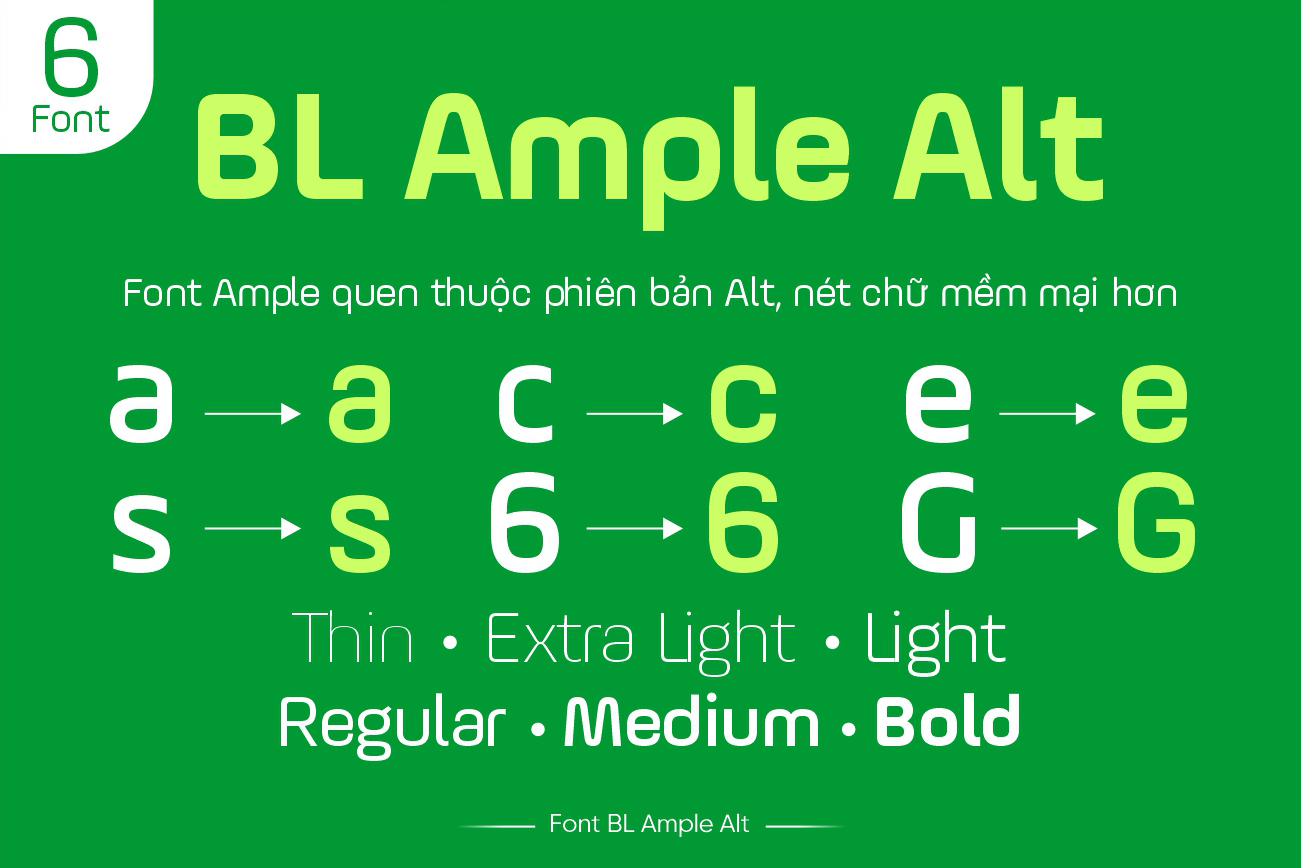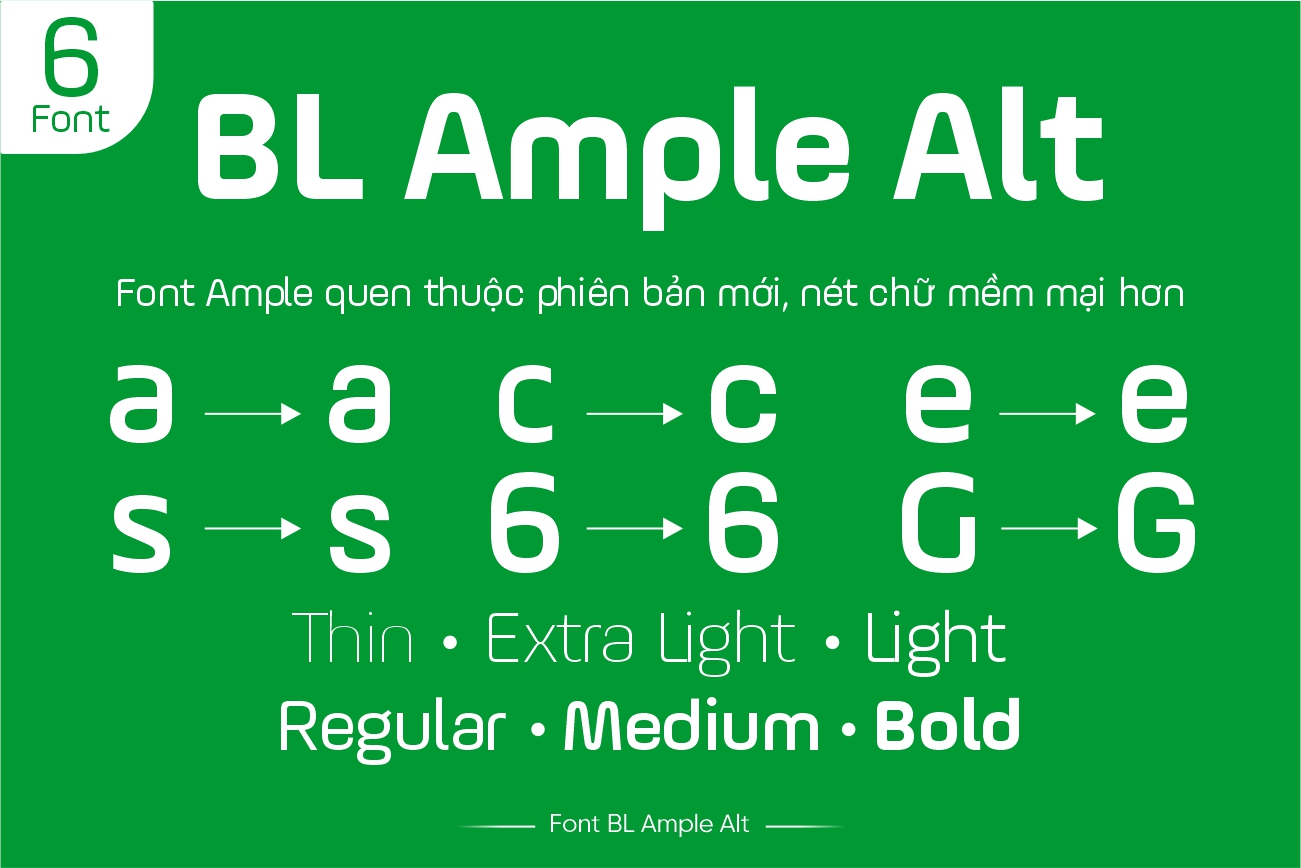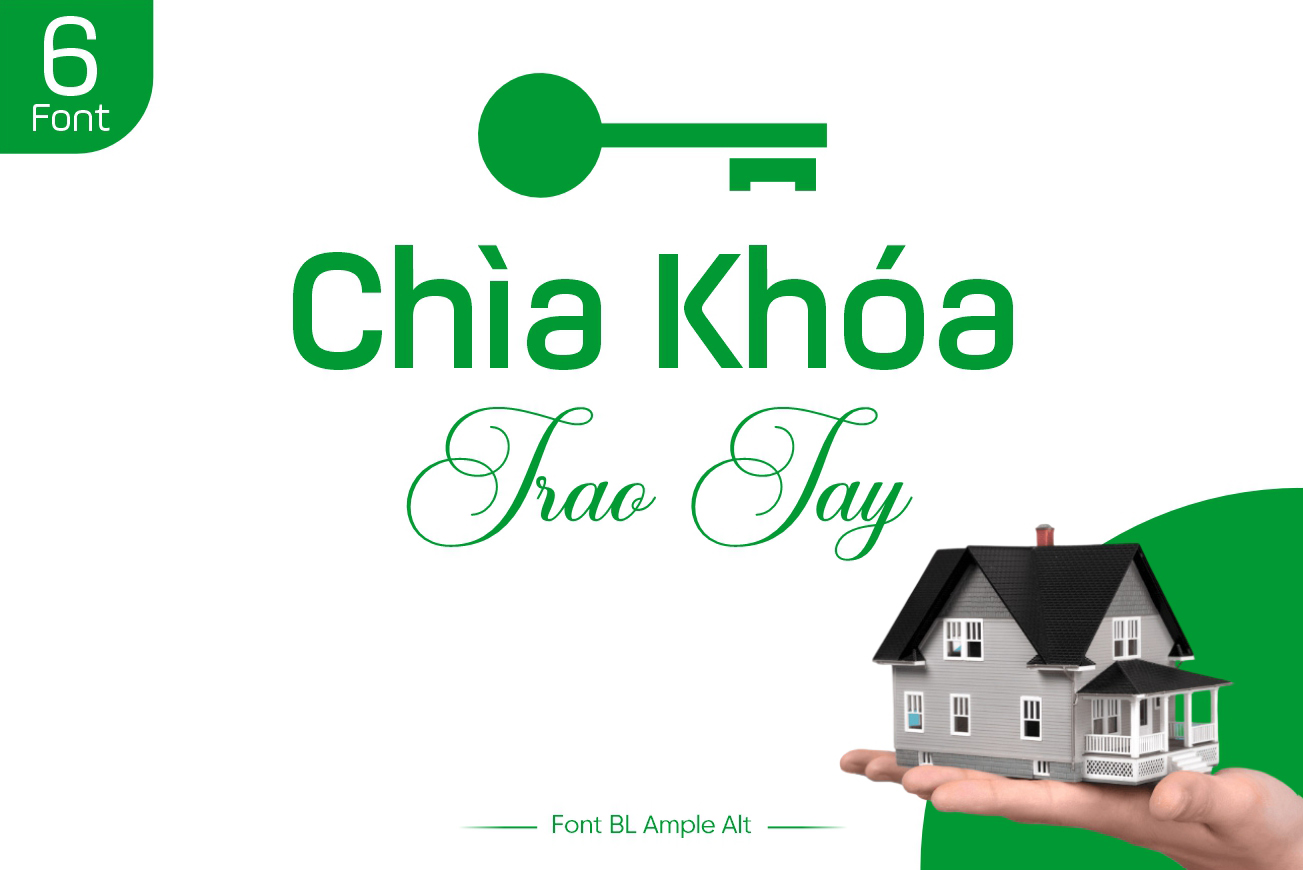
Bộ 6 font BL Ample Alt - Font công nghệ Việt hóa
Tác giả Soneri Type
BL Ample Alt là phiên bản Việt hóa từ bộ font Ample Alt do Soneri Type phát triển, thuộc họ Ample nổi tiếng với sự gọn gàng, trung tính và khả năng đọc dễ dàng trong nhiều ngữ cảnh thiết kế khác nhau. Đây là một font chữ san serif mang tinh thần hiện đại nhưng vẫn giữ được sự mềm mại, thân thiện nhờ những tinh chỉnh thông minh so với bản Ample tiêu chuẩn. Các chi tiết như độ cân chỉnh khoảng cách chữ, độ dày nét ổn định và cấu trúc hình khối rõ ràng giúp BL Ample Alt trở thành lựa chọn đáng tin cậy cho các nhà thiết kế, marketer, thương hiệu hoặc những ai đang cần một bộ chữ rõ ràng, chuẩn xác nhưng không khô cứng.
Điểm đặc biệt của BL Ample Alt nằm ở yếu tố “Alt – Alternate”, khi một số ký tự như a, g, y… được biến thể tinh tế để tạo cảm giác tự nhiên, linh hoạt và hiện đại hơn. Chính chi tiết này làm cho bộ font trở nên độc đáo hơn so với nhiều font chữ công nghệ khác, vừa mang hơi hướng kỹ thuật, chuẩn mực thiết kế, vừa tạo cảm giác gần gũi với người xem. Khi Team BL tiến hành Việt hóa, bộ chữ được tối ưu để hiển thị tiếng Việt đầy đủ dấu, sắc nét và cân đối, đảm bảo giữ trọn tinh thần thiết kế gốc nhưng vẫn phù hợp tuyệt đối với nhu cầu sử dụng tại Việt Nam.
Nhờ ưu điểm rõ ràng, BL Ample Alt đặc biệt phù hợp với website, giao diện ứng dụng, tài liệu thương hiệu, báo chí, poster hay thiết kế quảng cáo cần sự rõ ràng và chuyên nghiệp. Đây là lựa chọn lý tưởng nếu bạn đang tìm một font chữ nội dung sạch sẽ, dễ đọc, dễ ghi nhớ và thể hiện tốt tính hiện đại trong thiết kế.
Kết hợp hài hòa giữa phong cách font chữ san serif chuẩn mực và cảm giác thân thiện, BL Ample Alt mang đến trải nghiệm thị giác cân bằng, chuyên nghiệp và hiệu quả, giúp nội dung trở nên chỉn chu hơn và truyền tải thông điệp một cách rõ ràng, ấn tượng như một bộ font chữ công nghệ đúng nghĩa.